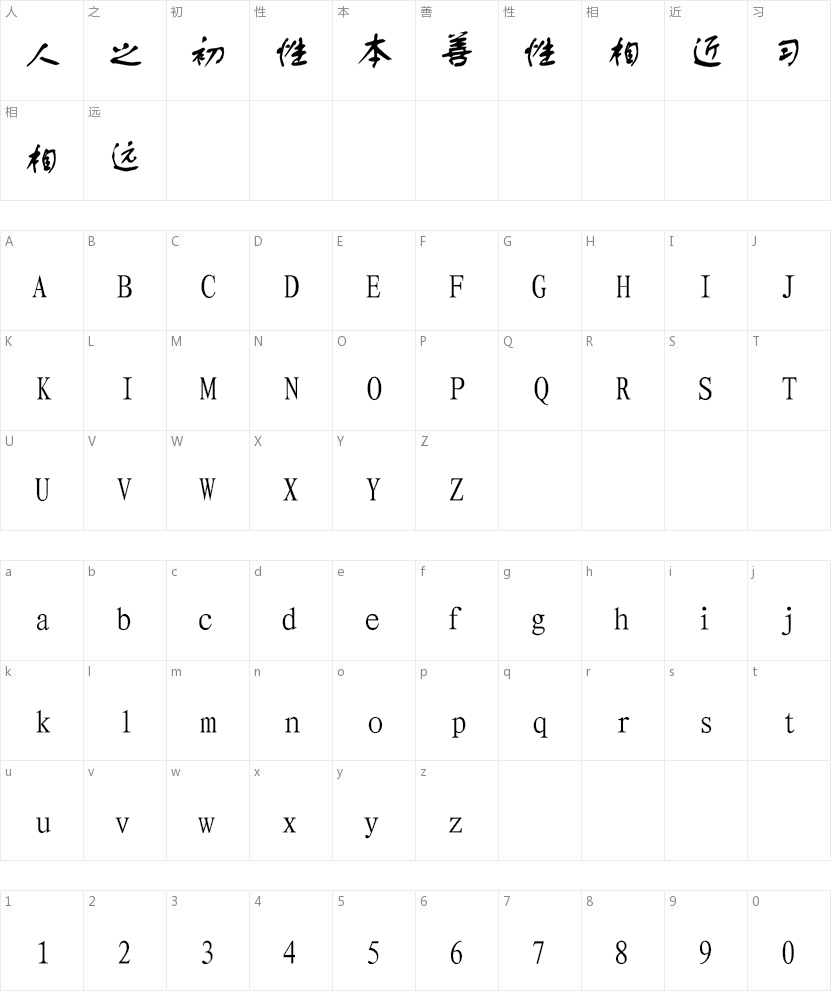
长城行书体
长城行书体是一种传统的中国书法字体,它源自于汉朝时期的行书,由汉朝书法家张旭发明,被称为“长城字体”。长城行书体以粗犷、稳重、挺拔的笔画为特点,被誉为“楷书中的行书”,被誉为“书法之冠”。长城行书体以楷书为基础,结合行书的风格,融入了楷书的规律性和行书的流畅性,形成了独具特色的行书形式。它以楷书的笔画为基础,以行书的风格为表达,以柔和的笔画为特色,以挺拔的笔画为特点,以流畅的笔画为特色,形成了独特的行书形式。
长城行书体是一款非常不错的手写艺术字体,具有很好的视觉感,适合于文化类的宣传设计、商业类品牌的广告和产品包装设计以及个性化文字排版等较多场景。